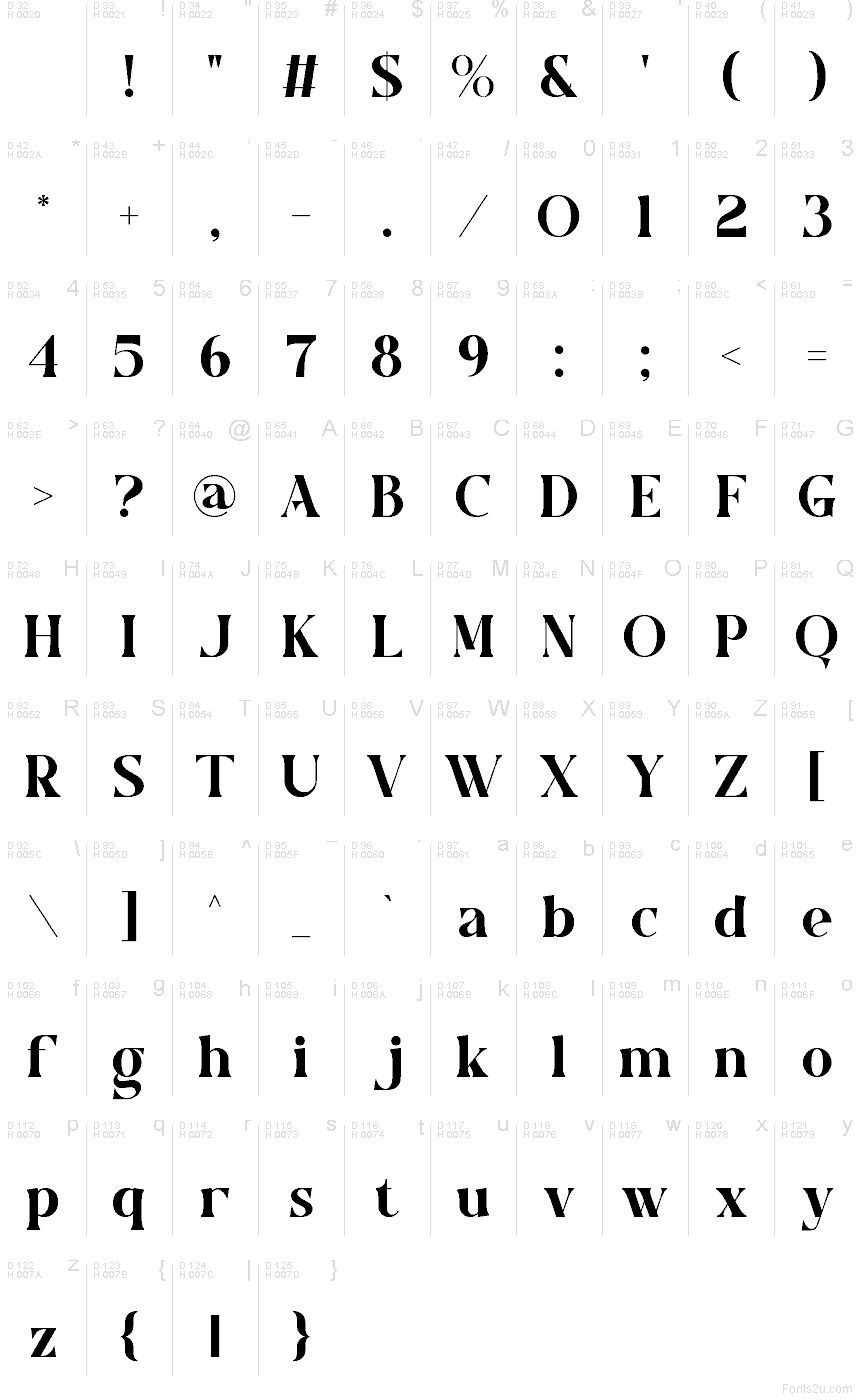
Faseon, de Ermedia Studio, é uma fonte serifada gratuita de alto contraste, com proporções visivelmente alongadas e um perfil dramático de moda editorial. Serifas pontiagudas e detalhes em gota afinam sua silhueta elegante.
As capas de revista são o seu ponto mais forte, mas suas linhas finas e curvas amplas também se adaptam a embalagens de perfumes, identidades visuais de moda e cartazes culturais. No design editorial, essa modulação acentuada entre traços grossos e finos pode transformar aberturas de seção e títulos de matérias em uma parte marcante e reconhecível da identidade de uma revista.